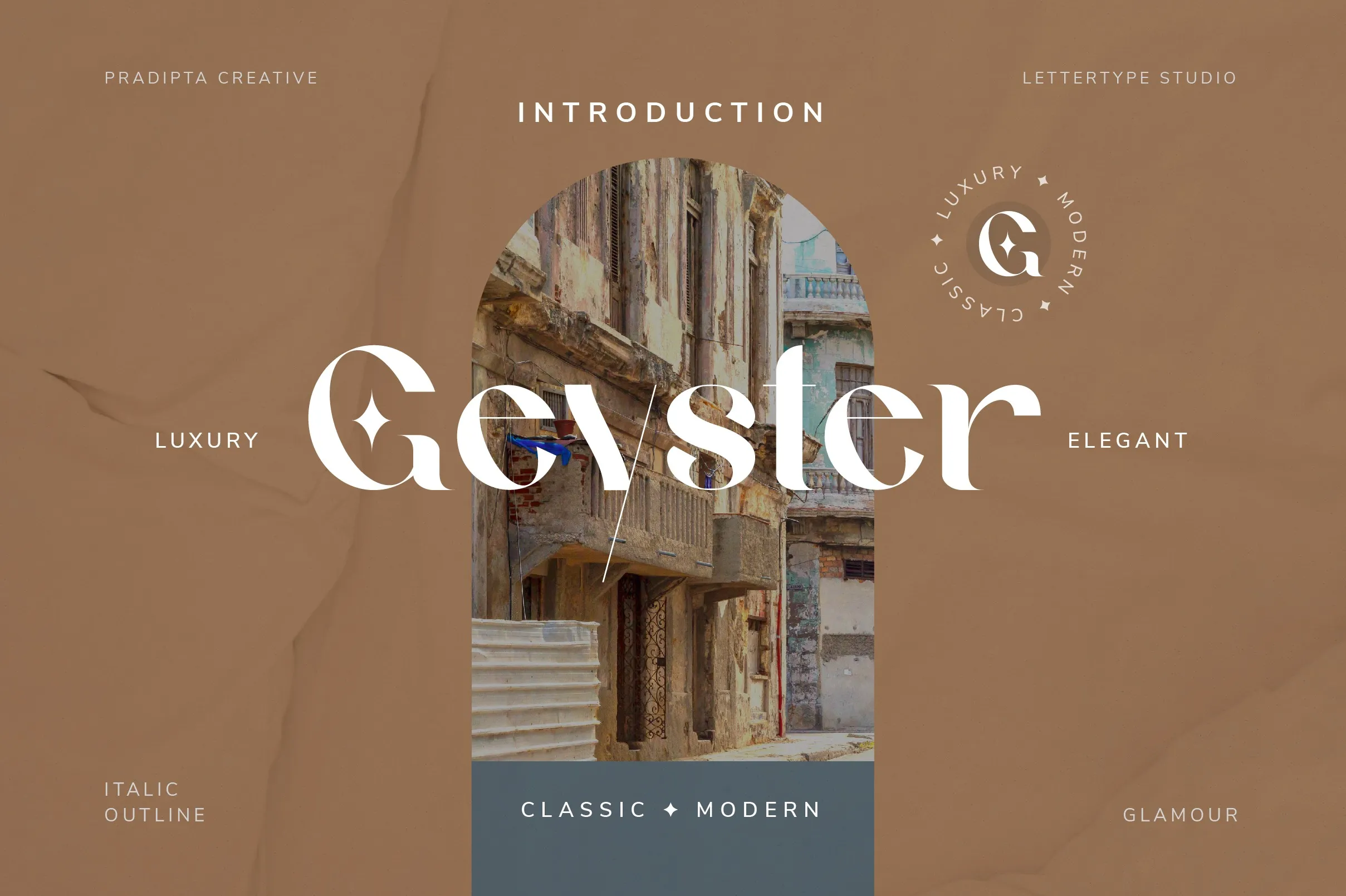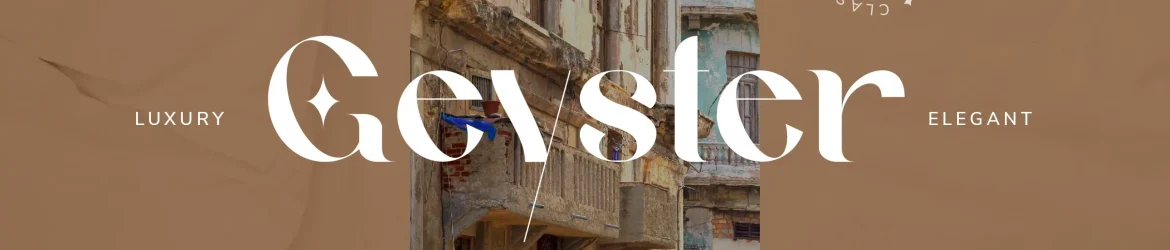
Geyster Font – Download Grátis
A Geyster Font é uma elegante serif que se destaca pela sua simplicidade e naturalidade moderna. Uma das suas características mais apreciadas é a sensação clara e limpa que transmite, tornando-a perfeita para uso em diversos tipos de materiais gráficos como logotipos, identidades corporativas, roupas, sinalização, cartazes, convites de casamento e muito mais. O seu criador procurou criar um mix entre serif moderno e clássico, com o objetivo de tornar suas criações ainda mais perfeitas e bonitas. Esta fonte é perfeitamente adequada para designers que desejam adicionar sofisticação aos seus projetos sem comprometer a elegância tradicional do tipo serif. A Geyster se encaixa perfeitamente no nicho de fontes serif, oferecendo uma opção única e moderna para estilos variados.